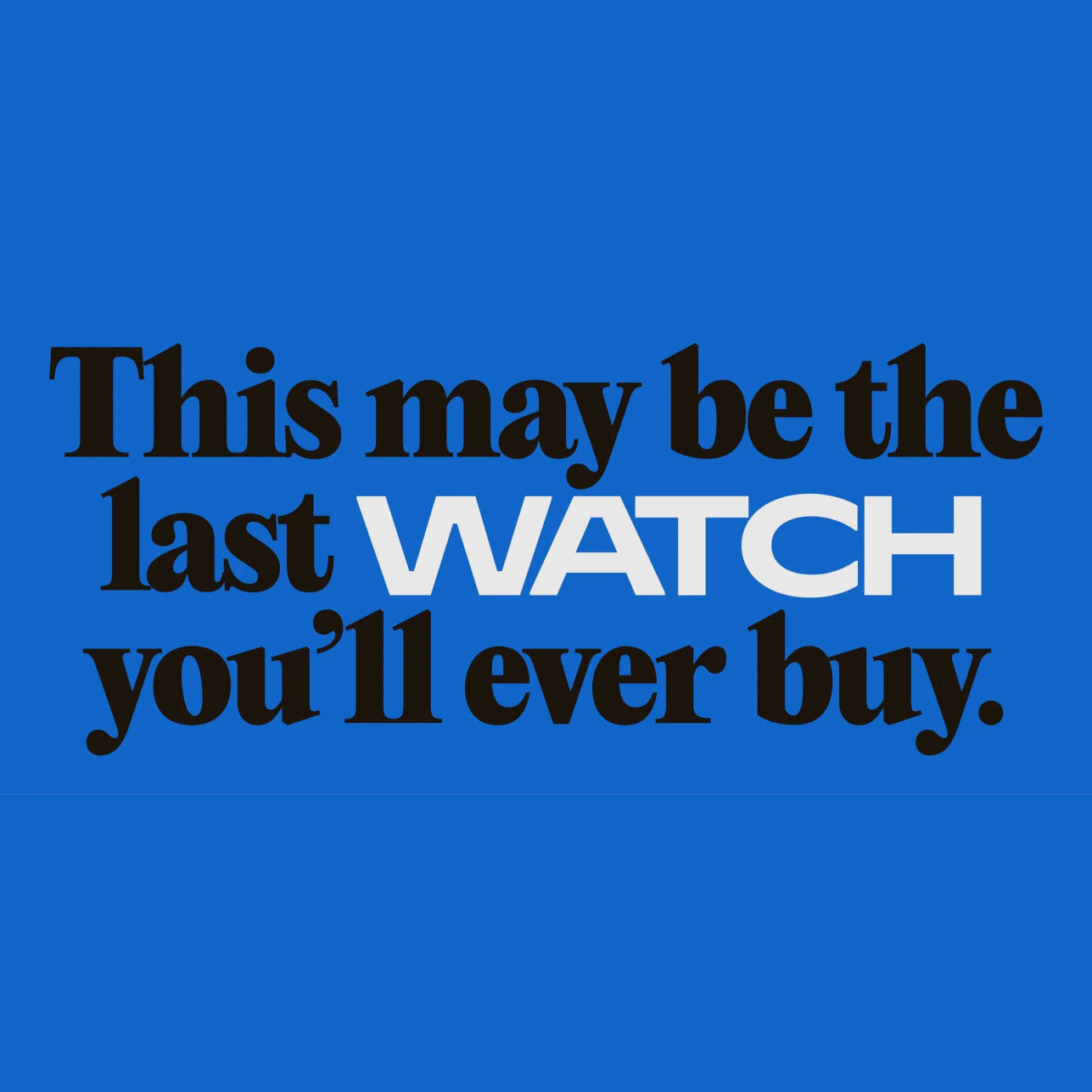
PP Watch est une police ancrée dans la précision. Et elle n'en est que plus ludique. Inspirée par les excentricités typographiques des cadrans de s vintage et l'élégance industrielle de la tampographie, elle offre un équilibre rare entre fonctionnalité pointue et charme analogique artisanal. Conçue par Niklas Herrmann, PP Watch arbore une silhouette large et un rythme affirmé, apportant une sophistication sculpturale à tout ce qu'elle habille, qu'il soit numérique ou imprimé. Mais comme pour toute grande , l'association parfaite fait toute la différence.
Pour vous donner une longueur d'avance, nous avons exploré cinq des meilleures polices qui complètent le ton, la structure et la personnalité de Watch, que ce soit par le contraste ou la cohésion. Ces associations ne sont qu'un point de départ ; alors, mélangez, assortissez et, surtout, expérimentez. À vous de jouer !
Incontournable de Pangram et classique moderne, Neue Montréal offre une base neutre et fonctionnelle qui permet à PP Watch de briller. Là où Watch est expressif et empreint de personnalité typographique, Neue Montréal maintient les choses en place grâce à sa logique directe et grotesque et à son généreux soutien linguistique. L'ensemble est à la fois éditorial, réfléchi et discrètement autoritaire. Structure et narration se rencontrent.
Pour les projets nécessitant une touche de personnalité supplémentaire, Right Grotesk est la police idéale. Avec ses proportions subtilement décalées et sa douce chaleur, elle s'accorde à merveille avec l'élégance sophistiquée de PP Watch. Le résultat est un dialogue entre deux polices qui jouent toutes deux avec les frontières de la tradition. L'une, avec ses empattements larges et ses détails mécaniques. L'autre, avec ses choix géométriques doux et ses excentricités inattendues.
Issue de notre fonderie sœur Off Type, Jubilee s'accorde parfaitement avec les nuances vintage de Watch. Conçue par Valerio Monopoli, Jubilee réinterprète le style institutionnel britannique à travers le prisme de Gill Sans et Windsor, offrant des proportions imposantes et une touche royale. Tandis que Watch évoque l'ingénierie, Jubilee est majestueuse et légèrement excentrique. Ensemble, elles dégagent une impression particulièrement mode et éditoriale, évoquant un esprit d'héritage, de savoir-faire artisanal et d'esprit graphique.
Partageant son ADN conceptuel avec PP Watch, Editorial New transpose les courbes classiques des années 70 et 80 dans un contexte éditorial précis. Utilisées ensemble, Watch et Editorial New font penser à deux membres d'une même famille : l'une avec empattement, l'autre sans empattement, toutes deux ultra-classes. Elles partagent le rythme, les proportions et un sens de la narration typographique, ce qui les rend idéales pour tout ce qui exige nuance, voix et style à parts égales.
Parfois, le meilleur duo se forme au sein d'une même famille. La PP Watch a été rigoureusement conçue avec la polyvalence comme point fort, ce qui en fait un choix idéal pour s'associer à elle-même. Avec huit graisses, chacune avec une italique assortie, vous pouvez créer une typographie dynamique et multicouche en jouant simplement sur les contrastes. Utilisez les graisses plus légères pour les textes longs ou les détails fins, et laissez les graisses noires ou extra-gras prendre le dessus pour les titres ou les appels à l'action percutants.
Mieux encore, utilisez la fonction d'alternances contextuelles pour alterner entre des formes épurées et modernes et des variantes à empattements inspirées des cadrans de traditionnels. Cela ouvre une palette d'expressions surprenante, vous permettant de passer d'ambiances utilitaires à ornementales au sein d'une même mise en page. Conçu pour l'élégance, la précision et la profondeur créative.